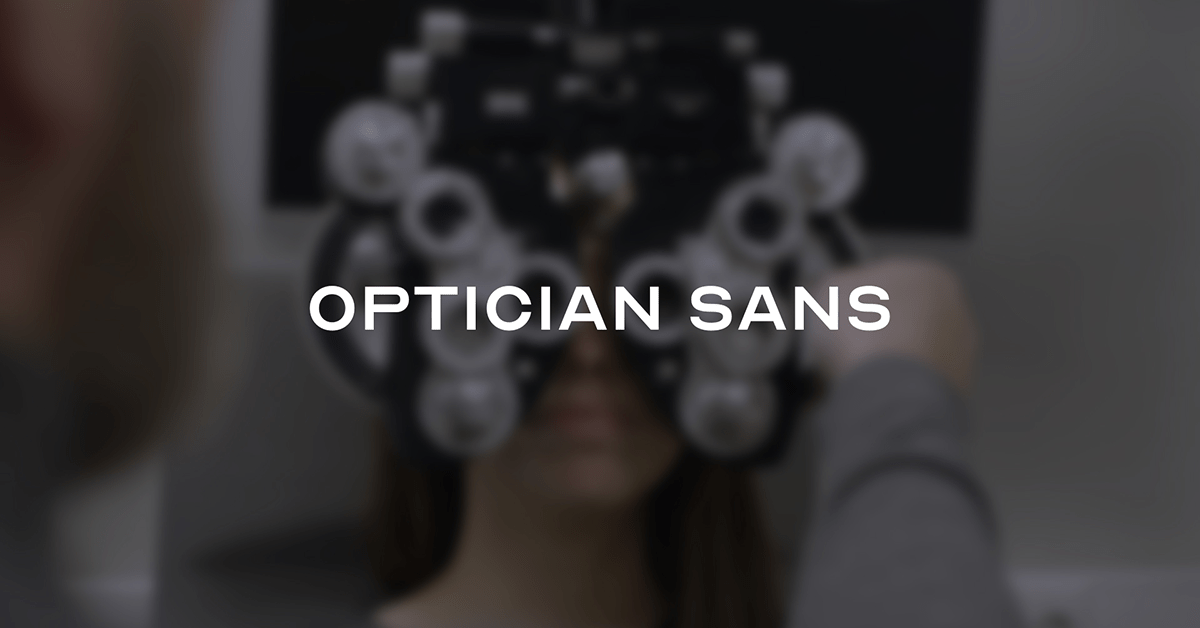
Optician Sans: la tipografía más legible del mundo
Esta tipografía ha sido diseñada tomando como modelo las pruebas optométricas usadas por oftalmólogos desde hace siglos
Cualquiera que haya pasado por la consulta de un oculista o se haya colocado detrás de esos aparatos metálicos llenos de lentes en una óptica habrá visto y leído una serie de letras escritas en negro sobre un fondo blanco que permiten a los expertos medir nuestra agudeza visual y prescribirnos lentes correctoras en caso de que las necesitemos. Optician Sans es una tipografía que imita las fuentes tradicionalmente utilizadas para este tipo de pruebas optométricas, aunque sus creadores han creado variantes de los diferentes glifos para poder adaptarla a los usos corrientes del diseño, incluida la creación de logotipos, motivo, por cierto, por el que este proyecto ha podido ver la luz.
La compañía Optiker-K pidió al estudio ANTI Hamar un rediseño de su imagen de marca y los diseñadores noruegos inmediatamente conectaron la idea con estos carteles, presentes en todas las ópticas del mundo, y se pusieron manos a la obra para desarrollar la tipografía. Para ello decidieron investigar quién y cómo había creado los primeros carteles de medición de agudeza visual. El primero de esos test lo diseñó el oftalmólogo neerlandés Herman Snellen en 1862, con un sistema que consistía en dibujar las letras sobre una cuadrícula en la que los espacios en blanco y los espacios en negro eran exactamente iguales. Desde entonces han existido dos gráficos estandarizados más: el de Louise Sloan, diseñado en 1959 y el LogMAR chart, creado en 1976 por el National Vision Research Institute de Australia.
Para diseñar Optician Sans se basaron en el sistema más primitivo y después de un largo proceso de debate, experimentación y desarrollo decidieron hacer una segunda versión de cada glifo para que pudiese adaptarse al uso de branding que pretendían darle. El resultado no podía ser más perfecto, legible y consistente; además, sus creadores han decidido compartir Optician Sans de manera completamente gratuita.
Optician Sans